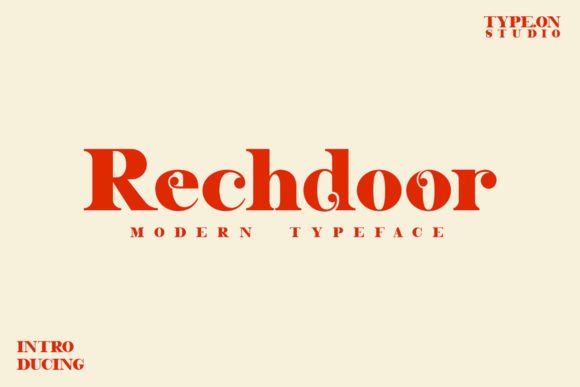
[Creativefabrica] Rechdoor Font (2021)
Rechdoor - смелый и модный шрифт с засечками.
Смело добавляйте его в свои любимые творения и позвольте себе поразиться полученному результату.